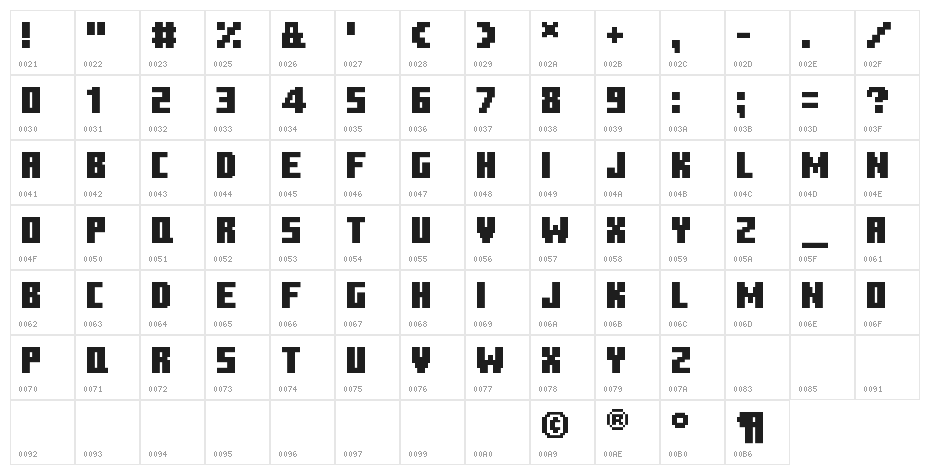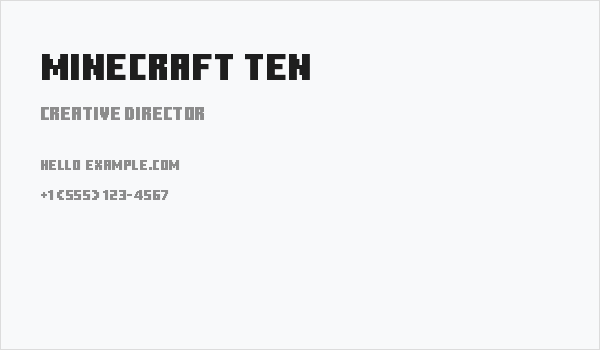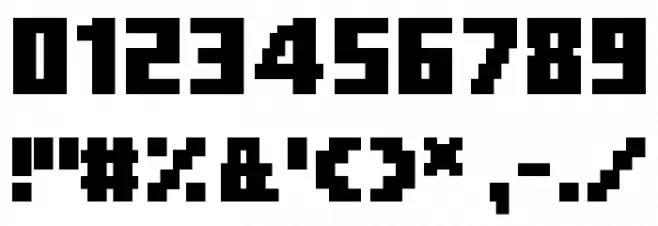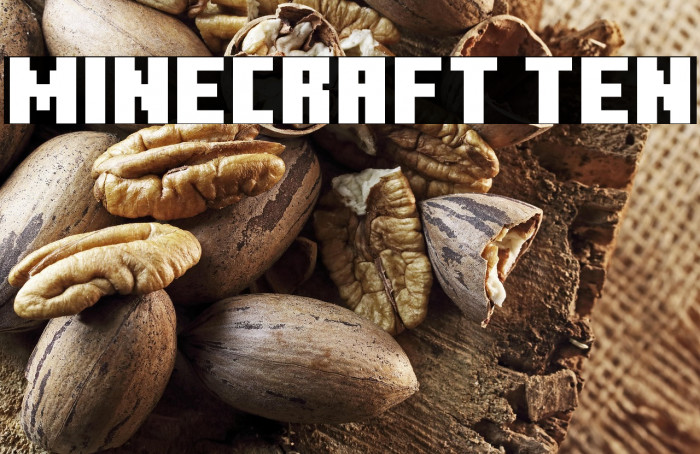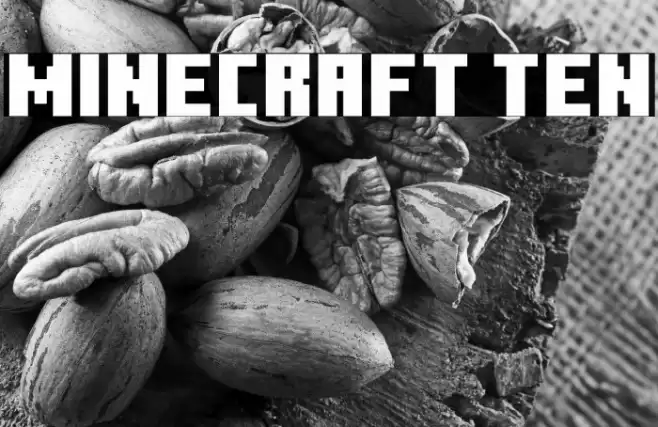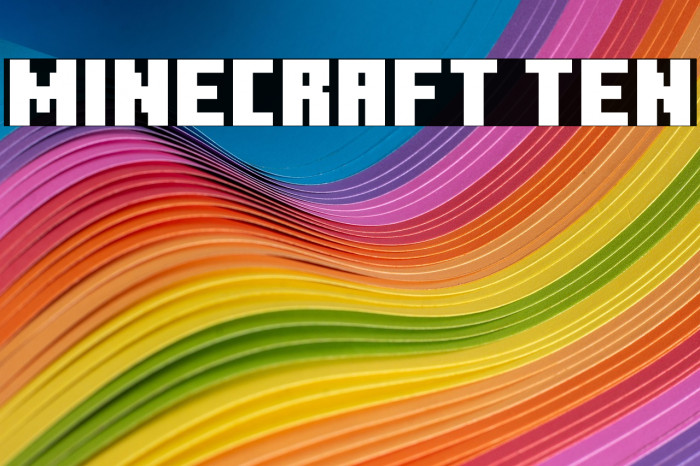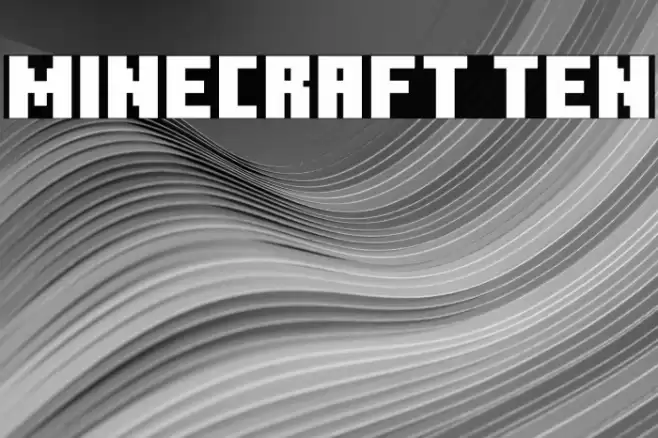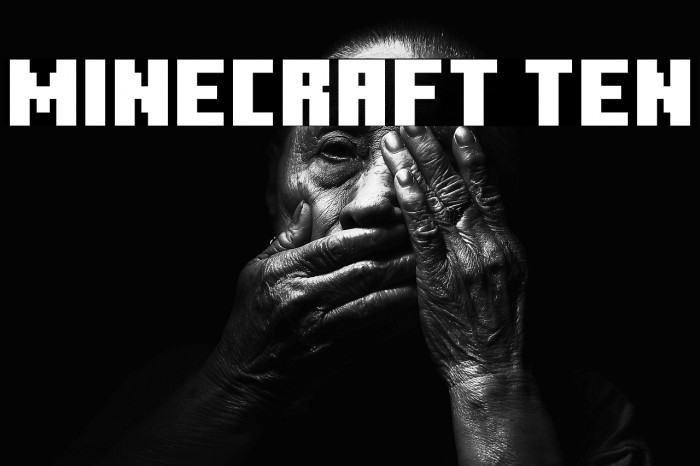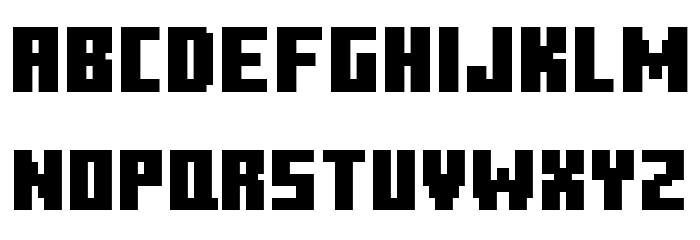
Minecraft Ten Font
✎ Pixel
| Estilo general | Retro, Digital |
| Caso de uso | Headlines, Logos, Digital Art |
| Proyectos propuestos | Ideal for video game design, retro-themed posters, digital art, and any project seeking a nostalgic or pixelated aesthetic. |